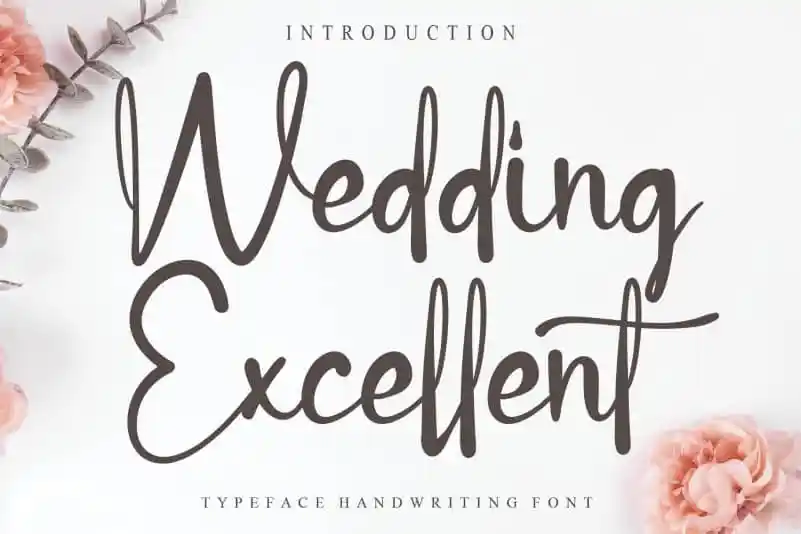
Wedding Excellent Script Font – Fonte Grátis
Wedding Excellent Script Font
Aqui está uma descrição em português para a página de download da fonte ‘Wedding Excellent Script Font’: Nossa fonte wedding “Excellente Script” é perfeita para criar mensagens carinhosas e românticas. Ela foi criada com detalhes meticulosos, ideal para cartões de casamento, lembrancinhas e até mesmo como uma forma criativa de escrever seus votos nupciais. Seu design elegante combina nuances delicadas e fortes elementos gráficos, proporcionando um resultado único e especial. Com a Wedding Excellent Script Font, você pode escolher entre várias opções de gama, garantindo que seu documento tenha uma aparência singular e memorável. Ideal para celebrar o amor com estilo. Esta fonte foi projetada especialmente por criativeletter, designer atento aos detalhes em uma variedade de formatos gráficos. Suas criações são frequentemente usadas para criar mensagens significativas em cartões e outros produtos personalizados, onde cada letra reflete um sentimento ou história única. Seja no design de cartão de casamento, na criação de embalagens de lembrancinhas personalizadas ou mesmo nas letras do seu próprio vídeo wedding, a fonte Wedding Excellent Script oferece uma maneira criativa e especial de expressar amor através da escrita.